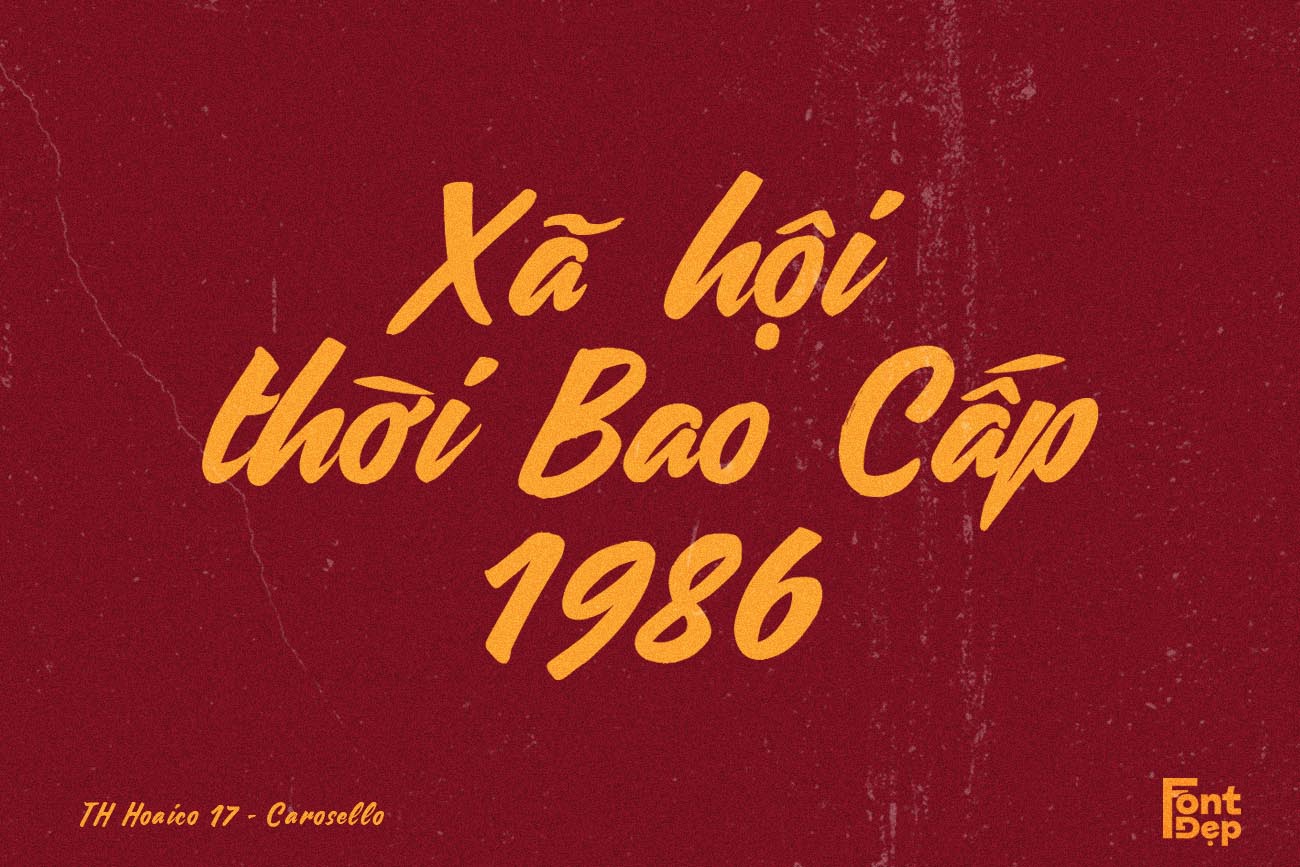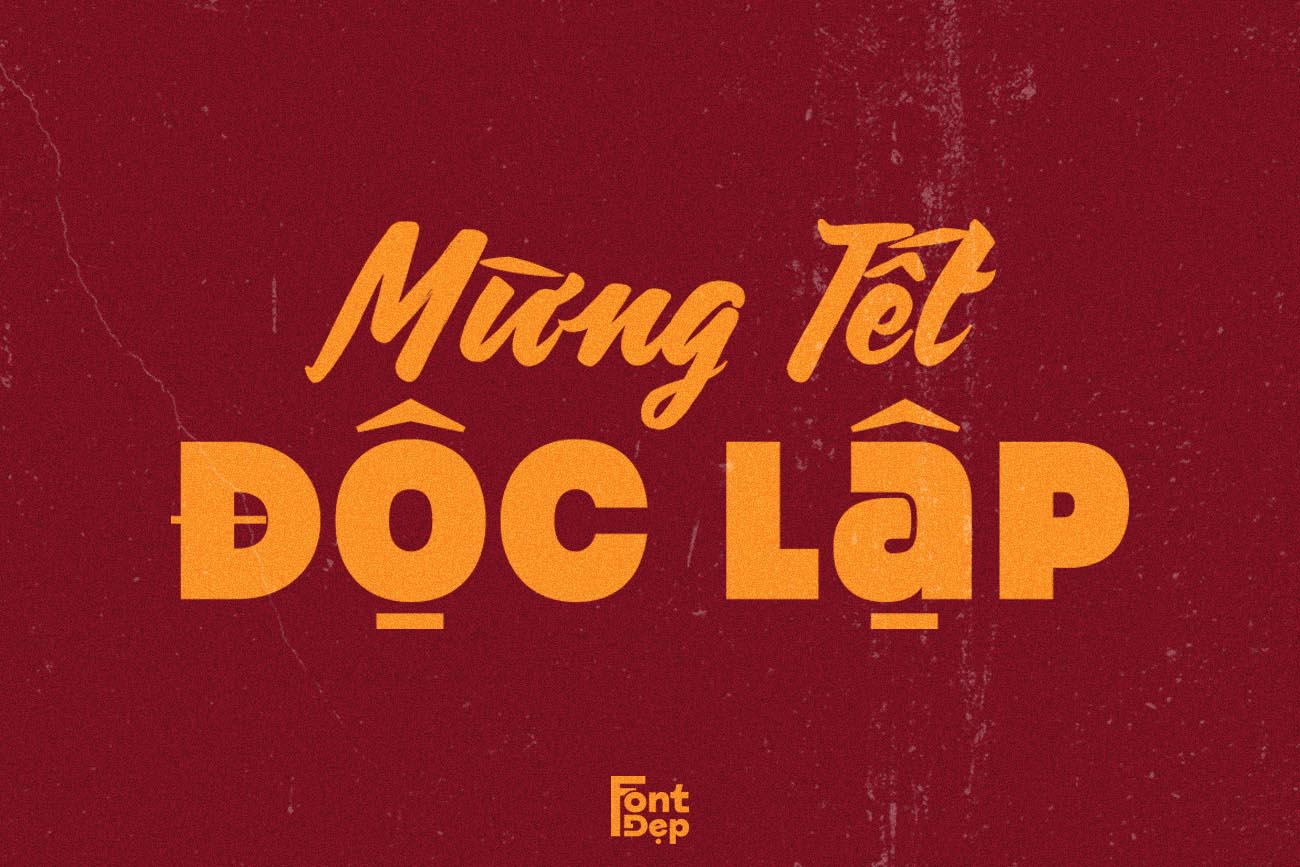
2 font chữ Sài Gòn xưa Việt hóa cho thiết kế bảng hiệu
Trong dòng chảy của thiết kế hiện đại, nhiều nhà thiết kế Việt Nam vẫn luôn tìm cách tái hiện tinh thần font chữ xưa để gợi nhắc về những ký ức thị giác một thời. Bộ đôi TH Hoaico 17 và TH Hoaico 63 là ví dụ điển hình, vừa mang lại sự hoài cổ của font chữ Sài Gòn xưa, vừa đủ tinh chỉnh để phù hợp với nhu cầu thiết kế hiện nay.
TH Hoaico 17 là font chữ nghiêng mềm mại, được Việt hóa từ font gốc Carosello. Font chữ này mô phỏng lại nét viết tay phóng khoáng của những tấm áp phích, bao bì, biển quảng cáo những năm 60–80. Kiểu chữ có độ bay bướm vừa phải, mang lại cảm giác gần gũi, gợi nhớ đến hình ảnh bảng hiệu xưa hay những câu khẩu hiệu treo dọc đường phố thời bao cấp. Điểm đặc biệt là phiên bản Việt hóa đã được bổ sung đầy đủ dấu tiếng Việt, giữ nguyên tinh thần phóng túng nhưng vẫn đảm bảo tính ứng dụng trong thiết kế hiện đại.
Ngược lại, TH Hoaico 63 mang phong cách vững chãi và mạnh mẽ hơn. Được Việt hóa từ font gốc Strenuous, kiểu chữ này có nét vuông vức, cứng cáp và dày dặn – rất giống với những font chữ bảng hiệu xưa từng thấy ở các cửa hàng mậu dịch, nhà văn hóa hay biển tên công cộng tại Việt Nam. Chính sự dứt khoát trong đường nét giúp TH Hoaico 63 phù hợp khi dùng cho tiêu đề, poster, banner hoặc những thiết kế mang hơi thở retro.
Sự kết hợp giữa TH Hoaico 17 và TH Hoaico 63 tạo nên một cặp đôi hoàn hảo: một bên uyển chuyển, gợi cảm xúc, một bên mạnh mẽ, gây ấn tượng thị giác. Khi phối hợp trong cùng một thiết kế, chúng giúp người xem ngay lập tức liên tưởng đến hình ảnh font chữ Việt Nam xưa, vừa quen thuộc vừa hoài niệm. Đây là lý do bộ font này rất phù hợp để làm poster triển lãm, thiết kế vintage, banner sự kiện hay bao bì gợi nhớ thời kỳ bao cấp.
Không chỉ mang tính chất thẩm mỹ, hai font còn là “cầu nối ký ức”, đưa những giá trị của quá khứ trở lại trong sáng tạo đương đại. Với tinh thần của font chữ cổ xưa được thổi hồn bằng công nghệ Việt hóa, TH Hoaico 17 và TH Hoaico 63 chắc chắn sẽ là công cụ đáng giá trong kho tư liệu thiết kế của bạn.